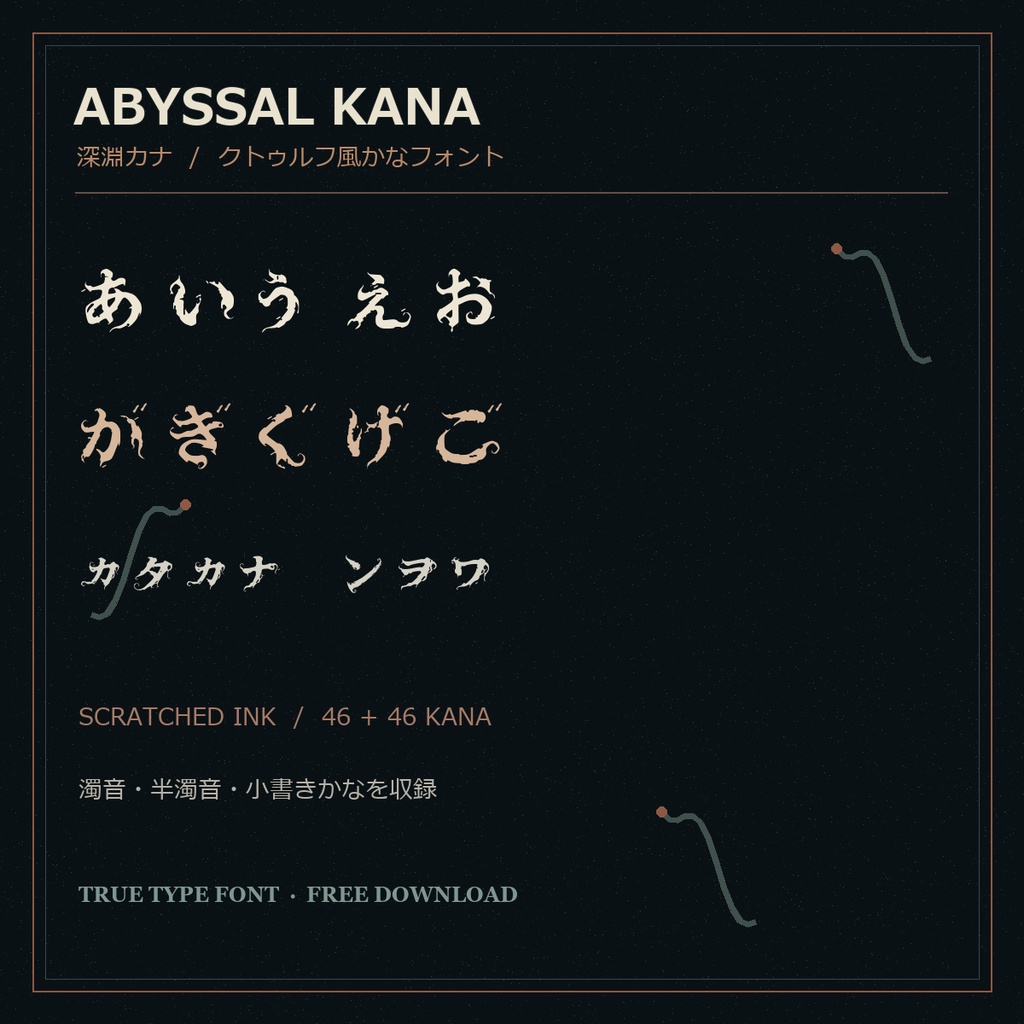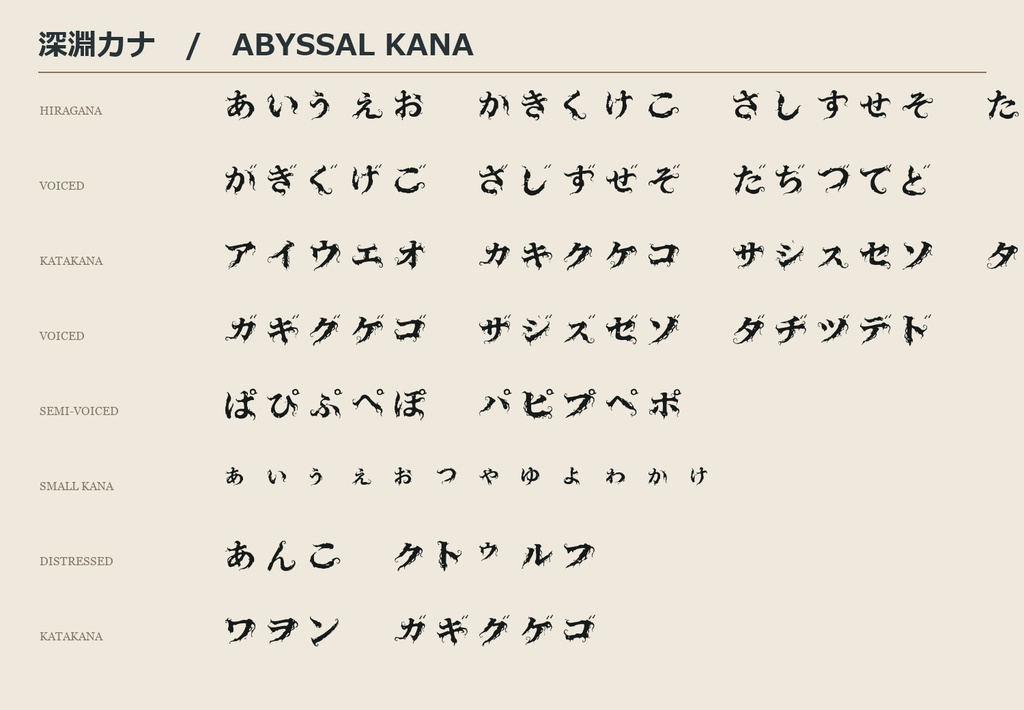
深淵カナ|クトゥルフ風ホラーかなフォント【無料】
クトゥルフ神話や宇宙的恐怖をイメージした、オリジナルのかな専用ディスプレイフォント「深淵カナ」です。文字の輪郭に爪痕、欠け、インク飛沫を加え、濁点と半濁点も触手を思わせる形に仕上げました。 ■ 収録内容 ・ひらがな46字、カタカナ46字(「ん」「ン」を含む) ・濁音、半濁音、小書きかな ・長音、句読点、中点、濁点、半濁点 ■ ファイル形式 TrueTypeフォント(TTF) ■ 利用規約 個人・商用作品の画像、映像、印刷物、ゲーム、配信素材、ロゴ等に利用できます。クレジット表記は不要です。フォントファイルの再配布、共有、改変版の配布・販売、第三者が取得できる状態でのWeb公開は禁止します。詳しい条件は同梱の「利用規約.txt」をご確認ください。 ■ ご注意 かな専用フォントです。漢字、英数字などは収録していません。見出し・タイトル向けの装飾書体で、小さいサイズの本文用途には向きません。特定のゲームや作品の公式フォントではありません。